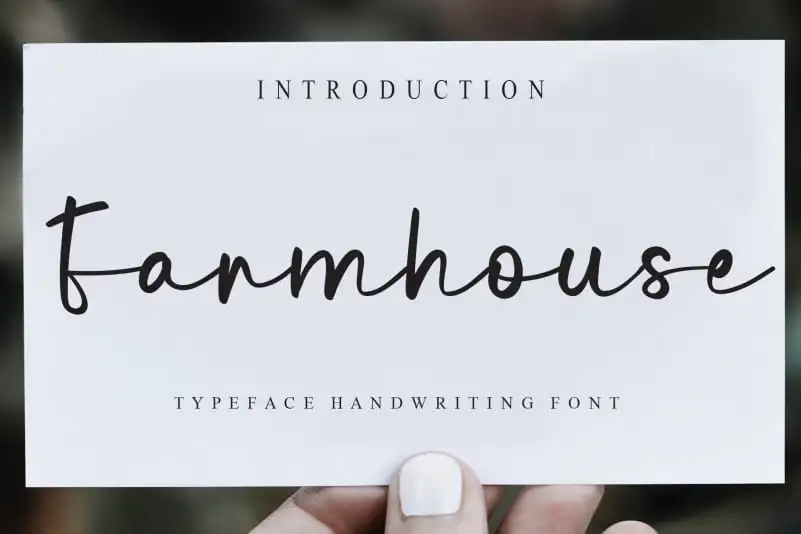
A Farmhouse Font é uma escolha perfeita para quem procura um estilo de escrita quase tão relaxante quanto a paisagem rural brasileira. Com sua tipografia cuidadosamente elaborada, criativa e única, esta fonte se adequa perfeitamente para qualquer projeto que deseje dar ao seu design um tom acolhedor e autêntico. Para os amantes da natureza, especialmente de nossa bela paisagem do Brasil, este estilo de letra é uma graça, proporcionando um toque natural em qualquer aplicação visual. Para os criativos, a Farmhouse Font oferece o detalhe perfeito para aqueles projetos que requerem um touch pessoal e autêntico. Suas linhas suaves e desenhadas com cuidado retratam o amadurecimento da terra brasileira, onde tudo se funde no horizonte do céu. Independentemente de seu uso em gráficos, design gráfico ou mesmo em textos de blog, esta fonte traz um ar de naturalidade e sofisticação aos seus projetos, tornando-a uma escolha indispensável para qualquer designer que deseja adicionar profundidade à sua identidade visual.